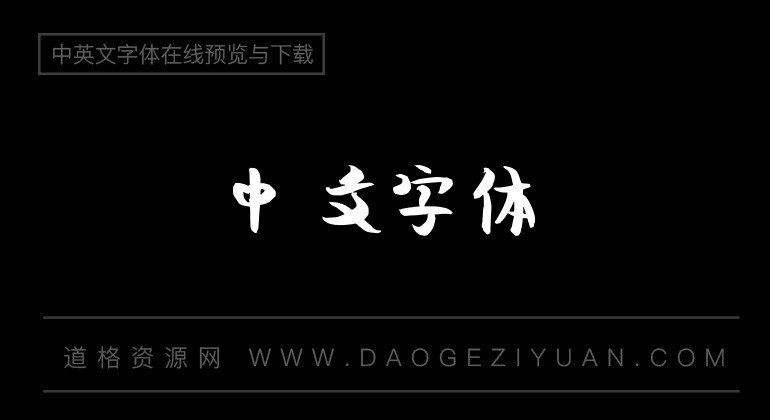
孙运和炫丽体
孙运和炫丽体是一款由中国字体设计师孙运制作的自由式字体,以其优雅而简洁的风格著称。字体以繁体字为基础,改变了字体的结构,使其变得更加流畅,更加有趣。它的字形特点是简练而清晰,笔画细腻而优雅,给人一种轻松悠闲的感觉。字体也可以在多种不同的应用程序中使用,如word、powerpoint、excel等等。
孙运和炫丽体是一款非常不错的手写艺术字体,具有很好的视觉感,适合于文化类的宣传设计、商业类品牌的广告和产品包装设计以及个性化文字排版等较多场景。